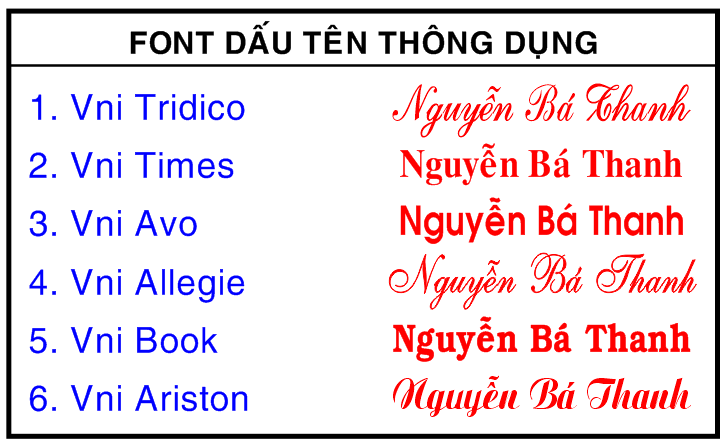
Font chữ con dấu là nhóm các phông chữ được tối ưu hóa đặc biệt để khắc dấu tên, con dấu tròn công ty, dấu vuông pháp lý hoặc tạo hiệu ứng đóng dấu mộc (rubber stamp) cổ điển trên các ấn phẩm bao bì. Với đặc trưng là cấu trúc chữ gọn gàng, độ rõ nét cực cao trong không gian hẹp hoặc mang hiệu ứng vệt mực mộc mạc, bộ phông chữ này là công cụ không thể thiếu cho dân văn phòng, thợ khắc dấu và các nhà thiết kế bao bì. Doozypack.vn cung cấp link tải trọn bộ font chữ con dấu Việt hóa chuẩn kỹ thuật, giúp bạn sở hữu các mẫu phông chữ sắc sảo, không lỗi dấu thanh để phục vụ công việc.
Phân loại các nhóm font chữ con dấu phổ biến hiện nay
Tùy thuộc vào mục đích sử dụng là làm con dấu pháp lý doanh nghiệp hay tạo hiệu ứng trang trí mộc mạc trên bao bì, bạn sẽ cần các nhóm phông chữ có đặc tính kỹ thuật khác nhau.
Font chữ con dấu tròn và vuông cho doanh nghiệp
Đối với việc thiết kế Font chữ con dấu tròn hoặc Font chữ con dấu vuông phục vụ cho pháp nhân công ty, các tiêu chuẩn đặt ra cực kỳ nghiêm ngặt. Phông chữ phải thuộc dòng Sans-serif hoặc Serif có nét đều, không quá mảnh nhưng cũng không quá dày, bảo đảm khi thu nhỏ trong đường kính vòng tròn từ 36mm đến 38mm, tên công ty và mã số thuế vẫn hiển thị rõ ràng, không bị bết mực khi khắc dấu.
Font chữ con dấu tên và làm mộc vintage
Nếu bạn đang tìm kiếm Font chữ con dấu tên hoặc Font chữ làm mộc tên để đóng lên thiệp cảm ơn, túi giấy Kraft, các dòng phông chữ mang hiệu ứng vết mực mộc (Rubber Stamp) sẽ là lựa chọn hoàn hảo. Nhóm này thường mô phỏng lại con dấu cao su thủ công với các vết hở mực ngẫu hứng, mang lại cảm giác hoài cổ, chân thực và đầy tính cá nhân hóa.
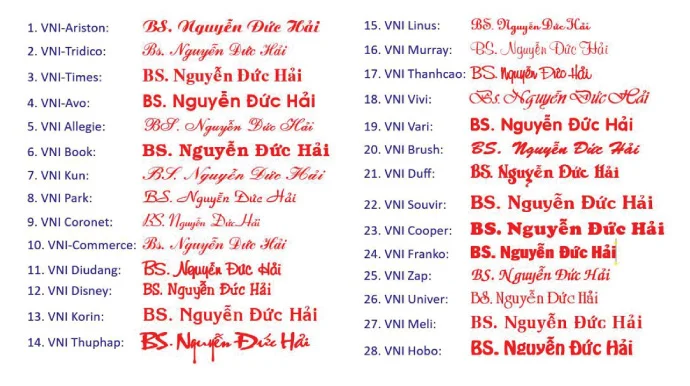
Ưu điểm nổi bật của bộ font chữ khắc dấu Việt hóa
Khi ứng dụng các phông chữ con dấu vào thực tế, sự chuẩn xác về mặt kỹ thuật và ngôn ngữ là yếu tố quyết định chất lượng con dấu:
- Hiển thị rõ nét trong không gian hẹp: Các phông chữ được tuyển chọn tối ưu hóa khoảng cách ký tự (tracking) và độ mở chữ (counter), giúp Font chữ khắc dấu tên không bị dính nét khi thu nhỏ.
- Hỗ trợ tiếng Việt hoàn hảo: Toàn bộ các dấu thanh (sắc, huyền, hỏi, ngã, nặng) và các ký tự đặc thù đều được Việt hóa chuẩn Unicode, giúp bạn khắc dấu họ tên người Việt một cách chính xác tuyệt đối.
| Nhóm Font | Đặc điểm thị giác | Ứng dụng đề xuất tại Doozypack.vn |
| Font Con Dấu Tròn / Vuông | Rõ nét, nét đều, chuẩn pháp lý | Thiết kế con dấu doanh nghiệp, dấu mã số thuế, dấu công ty. |
| Font Con Dấu Tên | Thanh lịch, trang trọng, dễ đọc | Khắc dấu tên cá nhân, chức danh, dấu chữ ký. |
| Font Đóng Dấu Mộc (Rubber) | Hiệu ứng vệt mực mộc mạc, Retro | Trang trí túi giấy Kraft, nhãn dán sản phẩm handmade. |
03 Ứng dụng thực tế của font con dấu trong sản xuất bao bì tại Doozypack.vn
Sự mộc mạc và chuẩn mực của các dòng phông chữ con dấu mang lại hiệu ứng thị giác đắt giá trên các ấn phẩm thực tế do Doozypack.vn sản xuất:
- Tem nhãn “QC Passed” & “Verified”: Sử dụng các mẫu Font chữ đóng dấu để in tem kiểm định chất lượng dán trên hộp sản phẩm, tạo sự tin cậy tuyệt đối cho người mua.
- Bao bì Kraft mộc mạc & Hộp trà: Đóng dấu mộc tên thương hiệu trực tiếp lên bề mặt túi giấy Kraft nâu tạo phong cách Vintage thủ công, nguyên bản và thân thiện với môi trường.
- Thiệp cảm ơn & Hộp quà tặng: Dùng Font con dấu để in lời chúc hoặc chữ ký cá nhân hóa bên trong hộp quà, giúp nâng tầm trải nghiệm mở hộp (unboxing) của khách hàng.
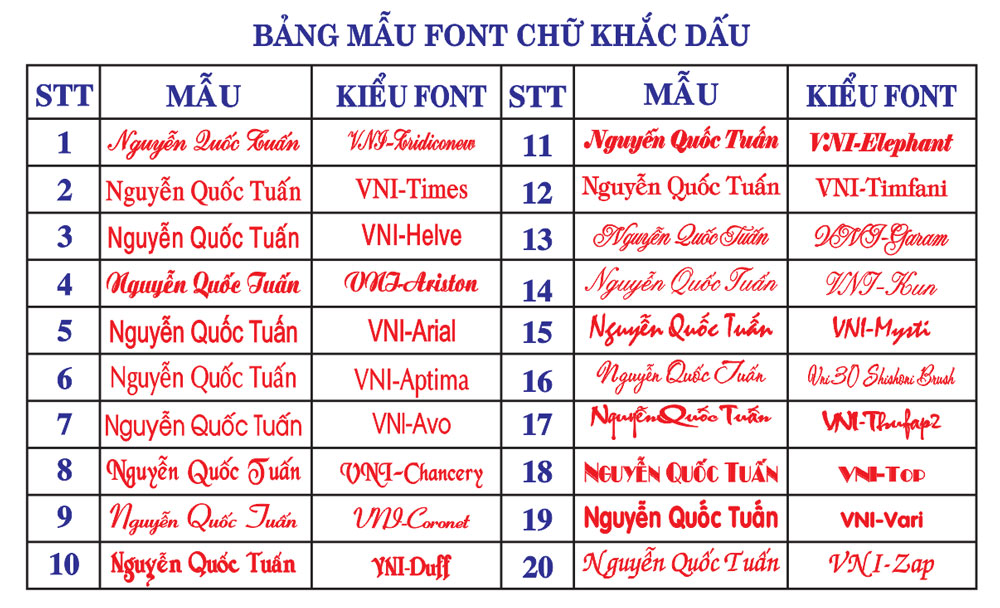
03 Lưu ý kỹ thuật khi thiết kế khắc dấu và in ấn tem nhãn
Việc sản xuất các ấn phẩm có sử dụng font con dấu đòi hỏi sự am hiểu kỹ thuật chuyên sâu tại xưởng in Doozypack.vn:
- Khoảng cách an toàn (Tracking): Đối với Font chữ khắc dấu tròn, các chữ cái xếp theo vòng cung thường dễ bị dính vào nhau ở phía trong. Bạn cần nới rộng khoảng cách chữ (Tracking) để con dấu sau khi khắc lên cao su không bị bết mực.
- Độ dày nét khắc: Tránh chọn các phông chữ có nét quá mảnh (hairline) cho con dấu đóng mực vì dấu sẽ nhanh mờ hoặc đứt nét. Hãy ưu tiên các biến thể Medium hoặc Bold.